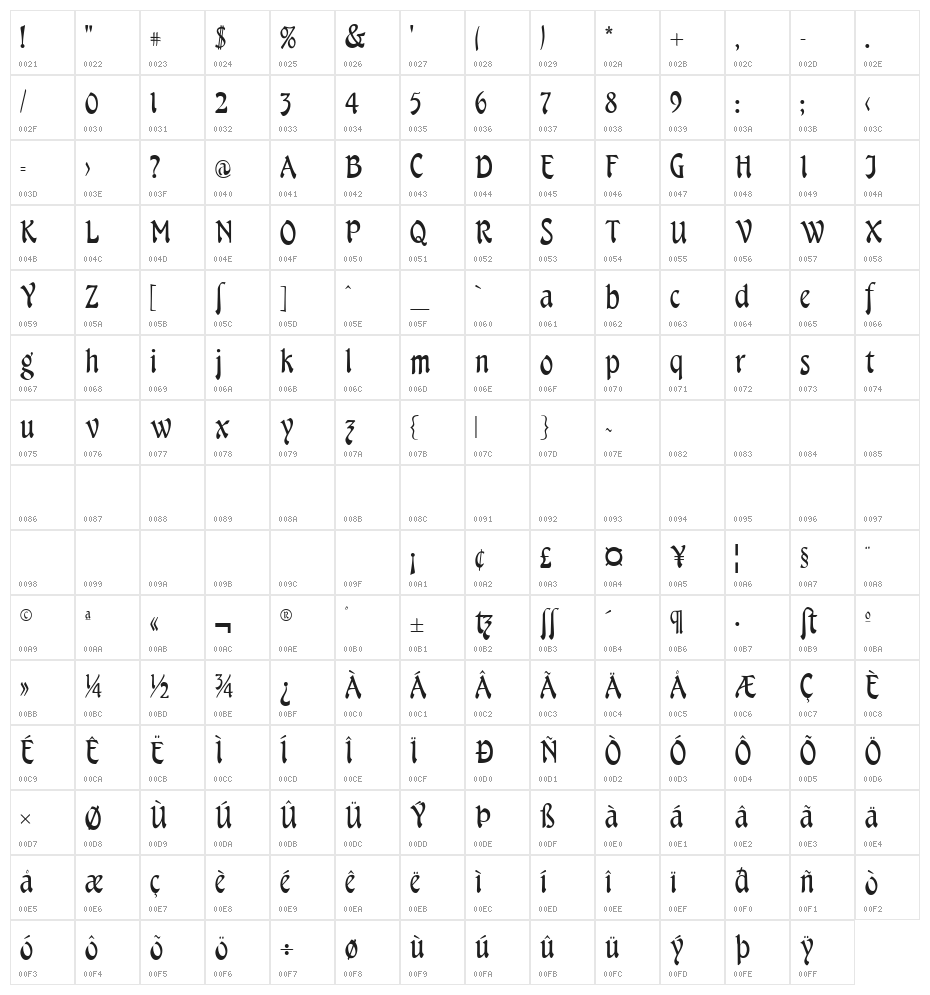
Menuetto Font
| Gesamtstil | Classic |
| Vorgeschlagene Projekte | Ideal for wedding invitations, historical documents, book covers, and branding that requires a classic touch. |